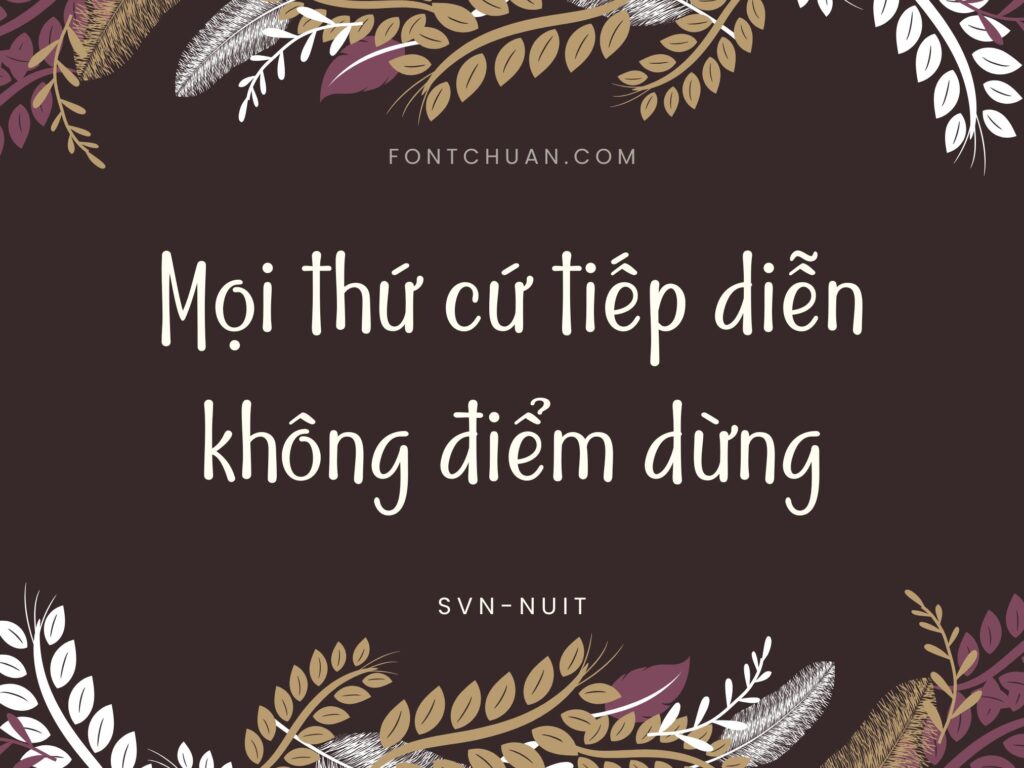
Font SVN Nuit Việt Hóa
Tác giả Font: Carine De Wandeleer
Font SVN Nuit là phiên bản Việt hóa của kiểu chữ Nuit, được thực hiện bởi STYLEno.1 Fonts. Nuit là một kiểu Font chữ viết tay thú vị với tính cách mạnh mẽ, được thiết kế bởi Carine de Wandeleer. Font này có độ nhảy nhẹ và sự không đều có chủ ý, mang lại cho văn bản một dòng chảy tuyệt vời. Sự kết hợp giữa nét đậm và mỏng trong các nét vẽ tạo nên một sự hài hòa ấn tượng. Nuit bao gồm đầy đủ các ký tự chữ hoa, chữ thường, chữ số và dấu câu, hỗ trợ đa ngôn ngữ. Font này phù hợp cho nhiều mục đích sử dụng khác nhau như thiết kế thiệp mời, logo, tiêu đề, bao bì sản phẩm và các ấn phẩm truyền thông.
SVN Nuit lý tưởng cho các dự án thiết kế yêu cầu sự vui tươi và thân thiện, như thiết kế thiệp mời, logo thương hiệu và các ấn phẩm truyền thông. Các ngành nghề như giáo dục, ẩm thực và thiệp cưới có thể tận dụng font này để tạo điểm nhấn trong thiết kế. Ngoài ra, font cũng thích hợp cho các sự kiện như Sinh nhật, Valentine, Tết và các lễ hội khác.